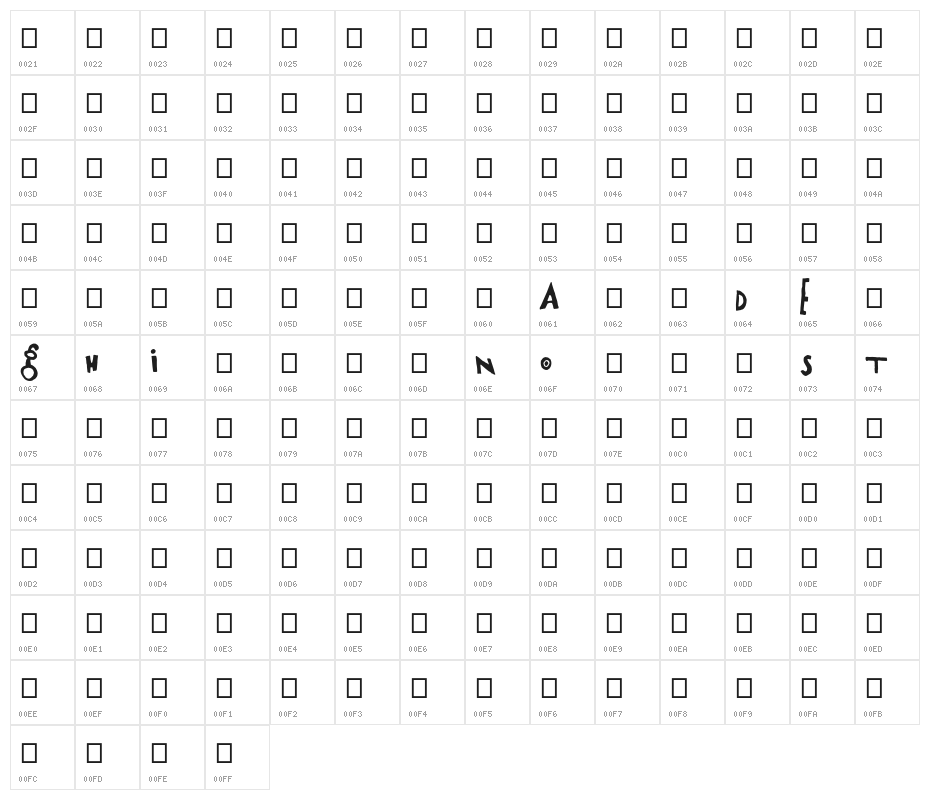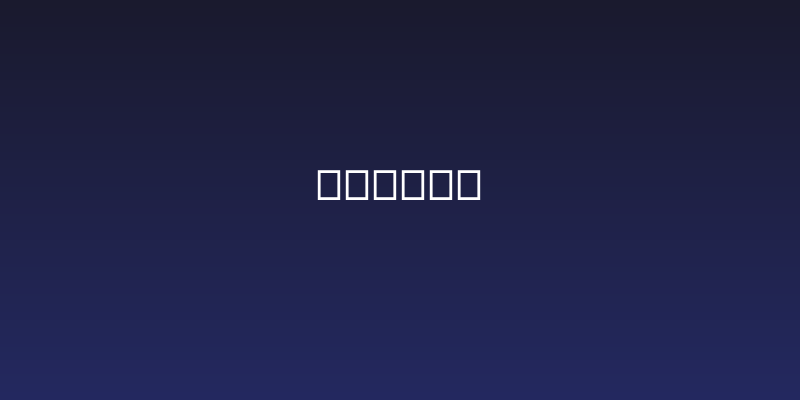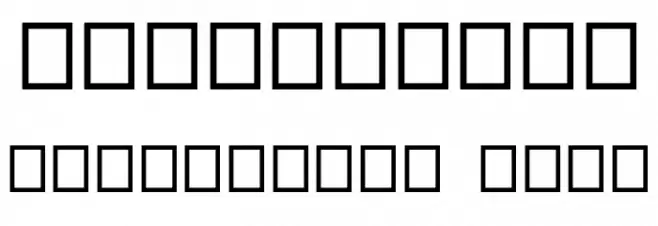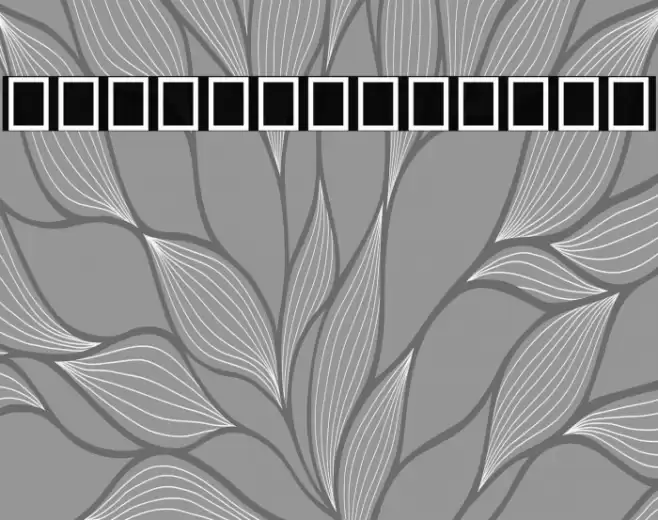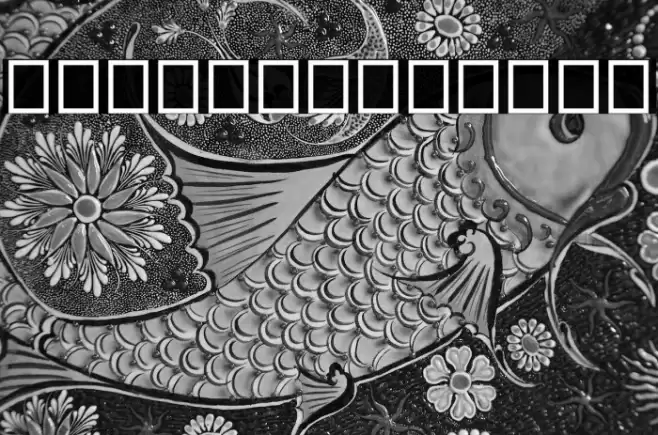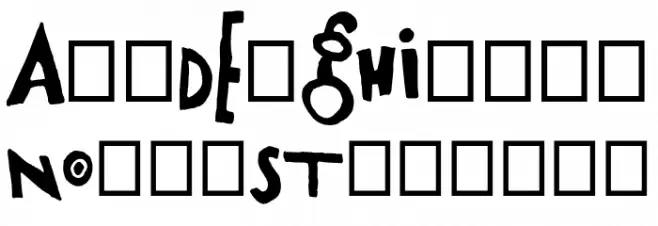
Airboy Font
Baby, I don't need dollar bills to have fun tonight
| Stile generale | Artistic, Graffiti-inspired |
| Caso d'uso | Headlines, Posters, Artistic designs |
| Progetti proposti | Ideal for creative projects such as posters, album covers, street art designs, and any work that benefits from a bold, artistic touch. |